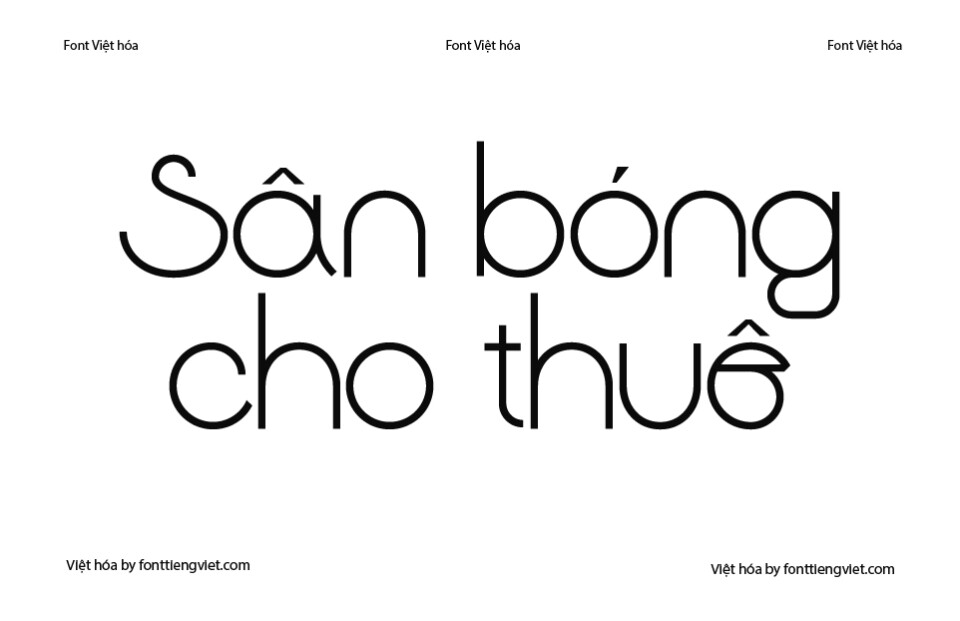
Font Việt hóa 1FTV VIP Gaego – Font Không Chân Mảnh Nhẹ Cho Thiết Kế Thể Thao
Giới thiệu về Font Việt hóa 1FTV VIP Gaego – Font Không Chân Mảnh Nhẹ Cho Thiết Kế Thể Thao
Trong thế giới đồ họa hiện đại, việc lựa chọn một Font Miễn Phí chất lượng là yếu tố then chốt để tạo nên sự chuyên nghiệp cho sản phẩm. Font Việt hóa 1FTV VIP Gaego – Font Không Chân Mảnh Nhẹ Cho Thiết Kế Thể Thao là một bộ phông chữ độc đáo, mang phong cách hiện đại và thanh thoát. Được thiết kế với các đường nét tối giản, bộ font này loại bỏ hoàn toàn các chi tiết rườm rà, giúp văn bản trở nên dễ đọc và thoáng đãng hơn. Đây là lựa chọn lý tưởng cho các nhà thiết kế đang tìm kiếm sự kết hợp giữa tính thẩm mỹ cao và khả năng ứng dụng linh hoạt trong nhiều dự án khác nhau, từ thương mại đến giáo dục.
Đặc điểm thiết kế của Font Việt hóa 1FTV VIP Gaego
Font Việt hóa 1FTV VIP Gaego sở hữu cấu trúc không chân (sans-serif) với độ mảnh đặc trưng, tạo cảm giác tinh tế và sang trọng. Các ký tự được tinh chỉnh kỹ lưỡng để đảm bảo sự cân đối, giúp truyền tải thông điệp một cách trực diện mà không gây rối mắt. Đặc biệt, phiên bản này đã được Việt hóa hoàn chỉnh, hỗ trợ đầy đủ các dấu tiếng Việt một cách chuẩn xác nhất, giúp người dùng không còn lo lắng về lỗi hiển thị khi soạn thảo nội dung dài hay làm tiêu đề ngắn.
Ứng dụng Font Việt hóa 1FTV VIP Gaego – Font Không Chân Mảnh Nhẹ Cho Thiết Kế Thể Thao
Đúng như tên gọi, Font Việt hóa 1FTV VIP Gaego – Font Không Chân Mảnh Nhẹ Cho Thiết Kế Thể Thao cực kỳ phù hợp cho các ấn phẩm liên quan đến vận động, sức khỏe và sự năng động. Sự nhẹ nhàng của các nét chữ giúp làm nổi bật các hình ảnh mạnh mẽ trong thiết kế thể thao mà không lấn át chủ thể chính.
Phù hợp cho banner và poster thể thao
Khi thiết kế các banner quảng bá giải chạy, poster phòng gym hay áo đấu, bộ font này mang lại cảm giác tốc độ và hiện đại. Độ mảnh của chữ giúp các nhà thiết kế dễ dàng chèn lên các nền ảnh phức tạp mà vẫn giữ được sự rõ ràng. Ngoài ra, nó còn rất phù hợp để làm typography cho các video giới thiệu sản phẩm công nghệ hoặc thời trang thể thao cao cấp.
Sử dụng trong trình chiếu và học tập
Đối với học sinh và giáo viên, việc sử dụng phông chữ này trong các bài thuyết trình giúp nội dung trở nên chuyên nghiệp và bắt mắt hơn. Sự tinh giản giúp học sinh tập trung tối đa vào thông tin truyền tải, giảm bớt sự mệt mỏi cho thị giác khi theo dõi bài giảng trong thời gian dài trên màn hình điện tử.
Lợi ích khi sử dụng Font Việt hóa 1FTV VIP Gaego
Kết luận về bộ Font Việt hóa 1FTV VIP Gaego
Hy vọng rằng Font Việt hóa 1FTV VIP Gaego – Font Không Chân Mảnh Nhẹ Cho Thiết Kế Thể Thao sẽ trở thành một công cụ đắc lực trong kho tài nguyên của bạn. Với sự kết hợp hoàn hảo giữa nét mảnh thanh lịch và tính hiện đại, bộ phông này chắc chắn sẽ làm thăng hạng các tác phẩm đồ họa của bạn một cách rõ rệt. Hãy trải nghiệm ngay Font Miễn Phí, Font Việt Hóa, Font Việt hóa 1FTV VIP Gaego – Font Không Chân Mảnh Nhẹ Cho Thiết Kế Thể Thao để cảm nhận sự khác biệt trong từng nét chữ và nâng tầm sáng tạo cho dự án thiết kế thể thao của mình ngay hôm nay nhé.